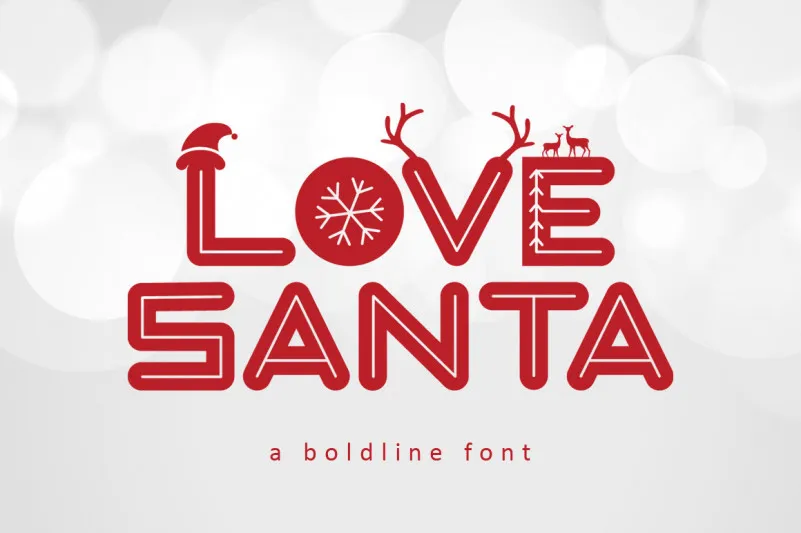
Love Santa Font for Christmas – Download Grátis
Descubra Love Santa Font for Christmas, uma fantástica fuçinha clássica para o Natal! Esta fonte sans serif traz ornamentos natalinos exuberantes, criando um único e inconfundível estilo de fontes do Natal. Ideal para dar uma pitada de festa a qualquer projeto gráfico, seja em cartões de aniversário, calendários ou até mesmo em logotipos. Add some jolly Christmas vibes ao seu design com este divertido fonte natalino! Desenvolvida pela ilustvara, Love Santa Font for Christmas é uma ótima opção para decorar seus projetos durante as celebrações festivas.